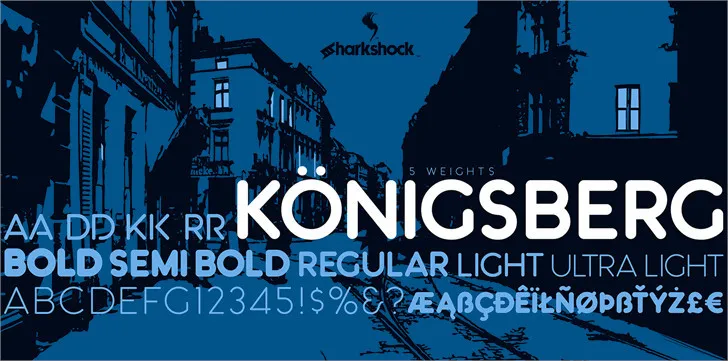
A Königsberg é uma elegante fonte que combina perfeitamente com os estilos modernos e sofisticados do nosso catálogo. Desenvolvida por Dennis Ludlow, esta fonte oferece um conjunto variado de opções que vão desde a simplicidade do Lightweight até a robustez da Bold. Seja para gráficos digitais ou projetos impressos, essa família de fótons proporciona uma solução visual única e moderna. Com o lançamento desta família de fótons na categoria Font Categories, você terá ao seu dispor uma fonte com um design moderno e moderno que se adapta a qualquer projeto. As opções de peso da regular até Ultra Light fornecem flexibilidade suficiente para atender aos mais variados requisitos estéticos. Esta é uma excelente oportunidade para aqueles que buscam uma fonte poderosa e versátil que ofereça um toque de sofisticação a qualquer projeto gráfico. A Königsberg é certamente uma fonte ideal tanto para designers digitais quanto para editoras de produção gráfica.
Designer: Sharkshock